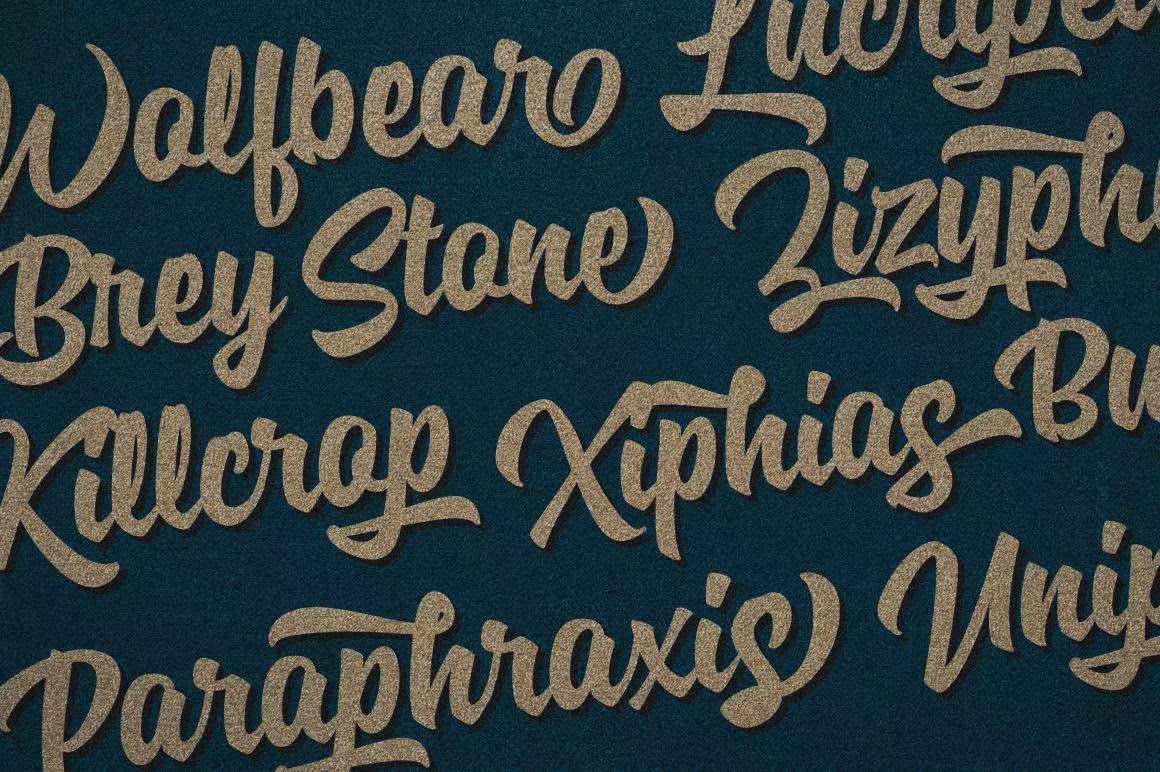
Spect Typeface灵感来源于RetroStyle,并结合了手写体风格。我认为个人风格会触动每一条曲线。我希望这能从你的工作中激发你的灵感。每一条漂亮的基线都能完美地完成对MarkerFont的恭维,以及对BonusWash的赞美。理想的日志、手写报价、产品包装、标题、海报、商品、,社交媒体和问候卡。由RetroStyle和手写字体相结合激发的SpectaTypeface。我的个性让我接触到每一条曲线。我希望这能让你从工作中获得灵感。每一条漂亮的基线都有完美的装饰性标记字体,以及超高和超高的Bonusswash。理想的日志、手写引号、产品包装、标题、海报,商品、社交媒体和问候卡。